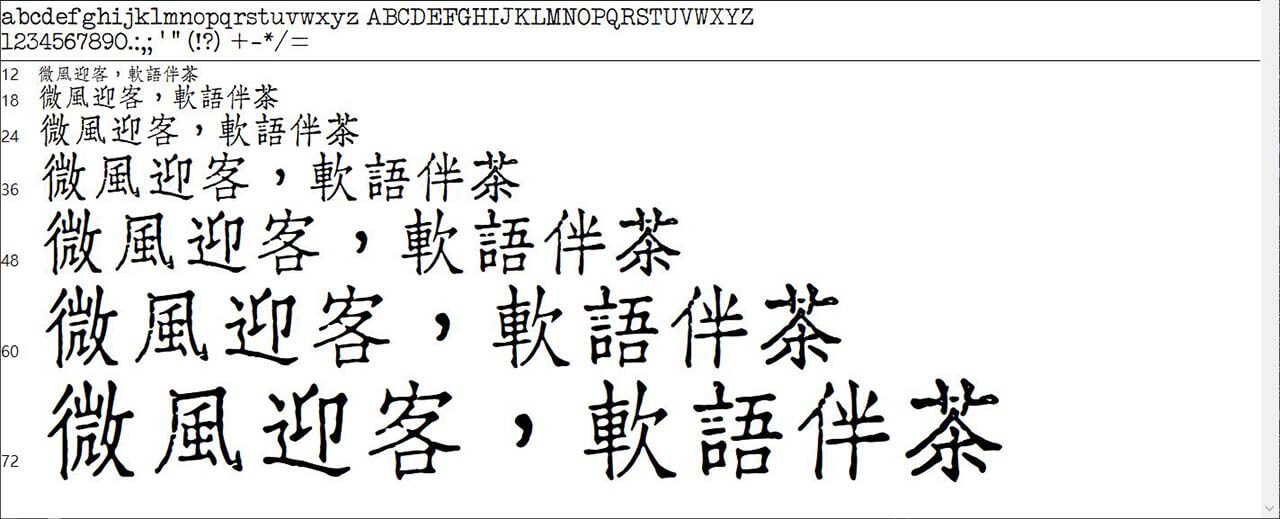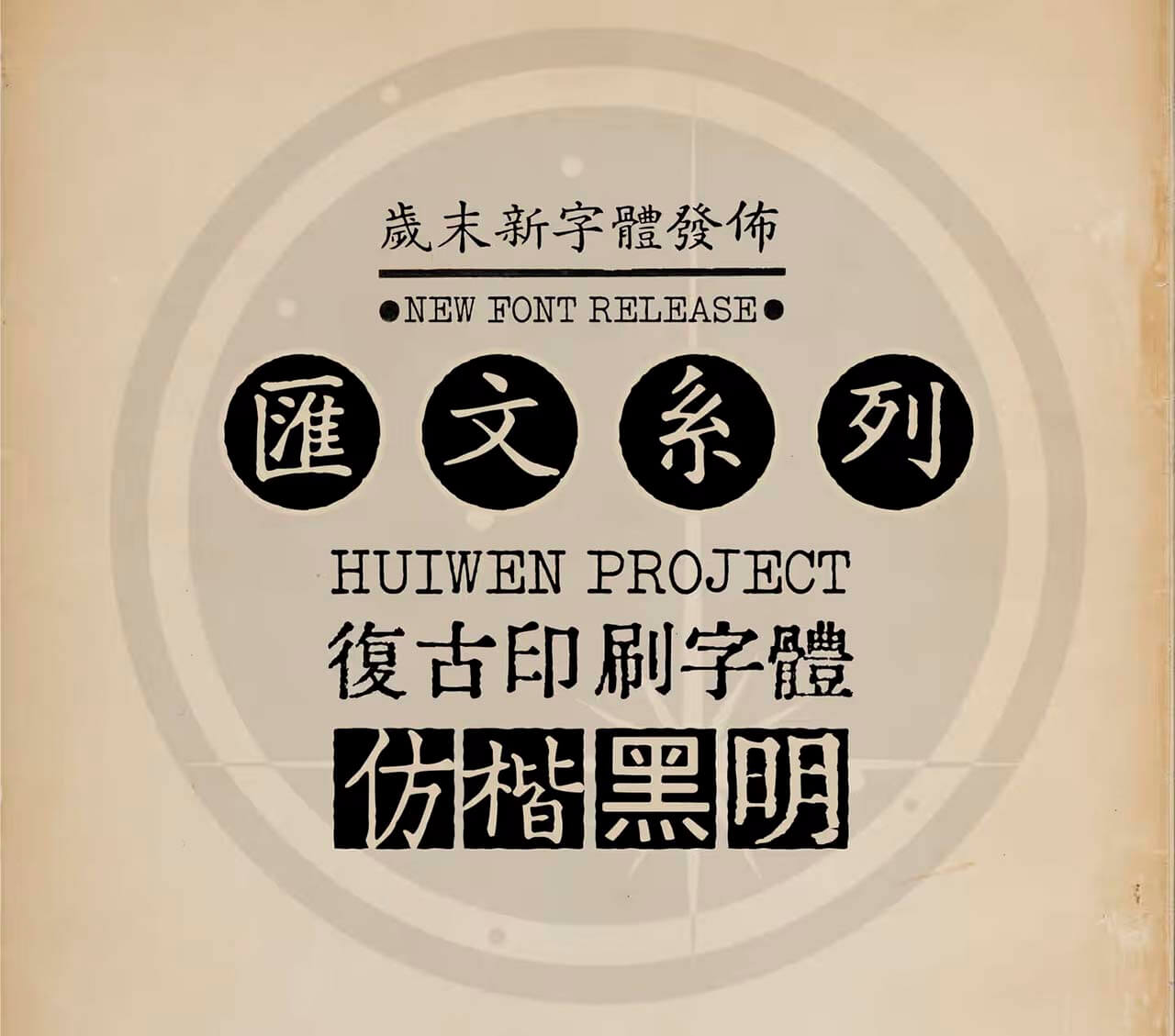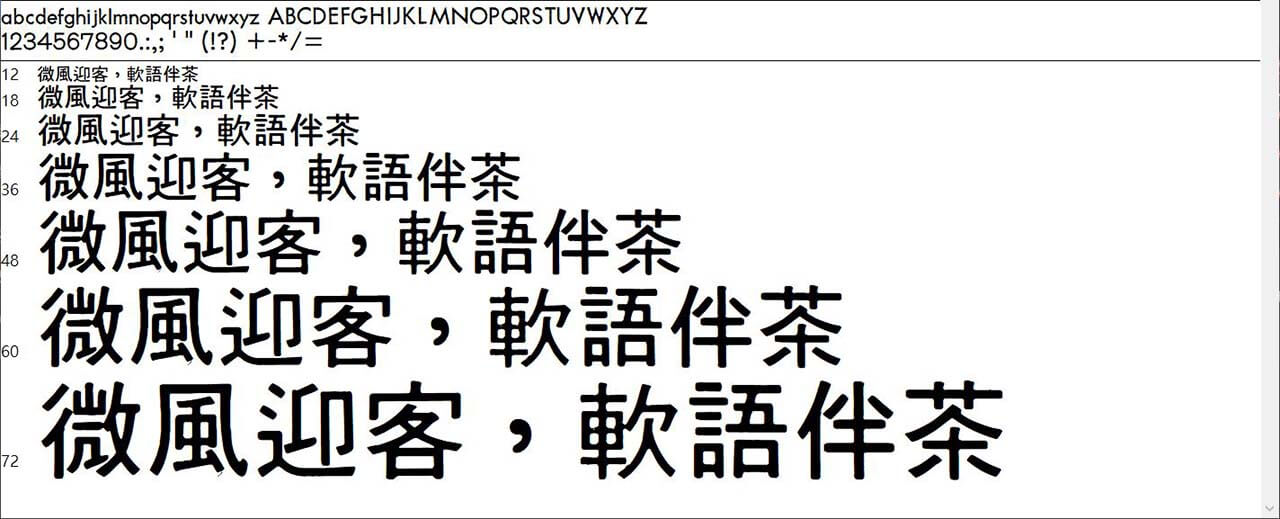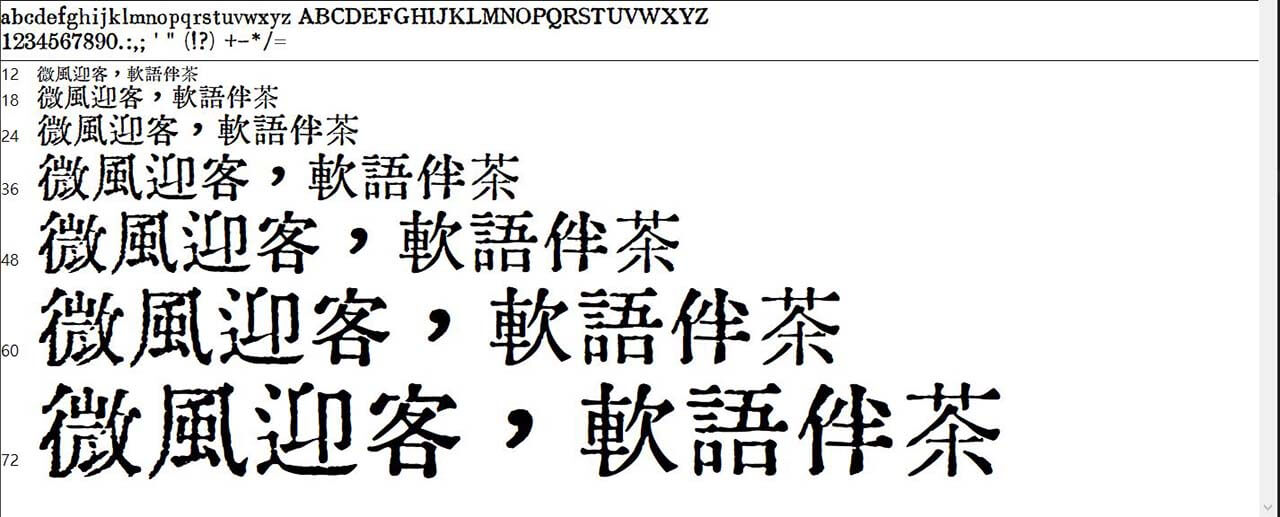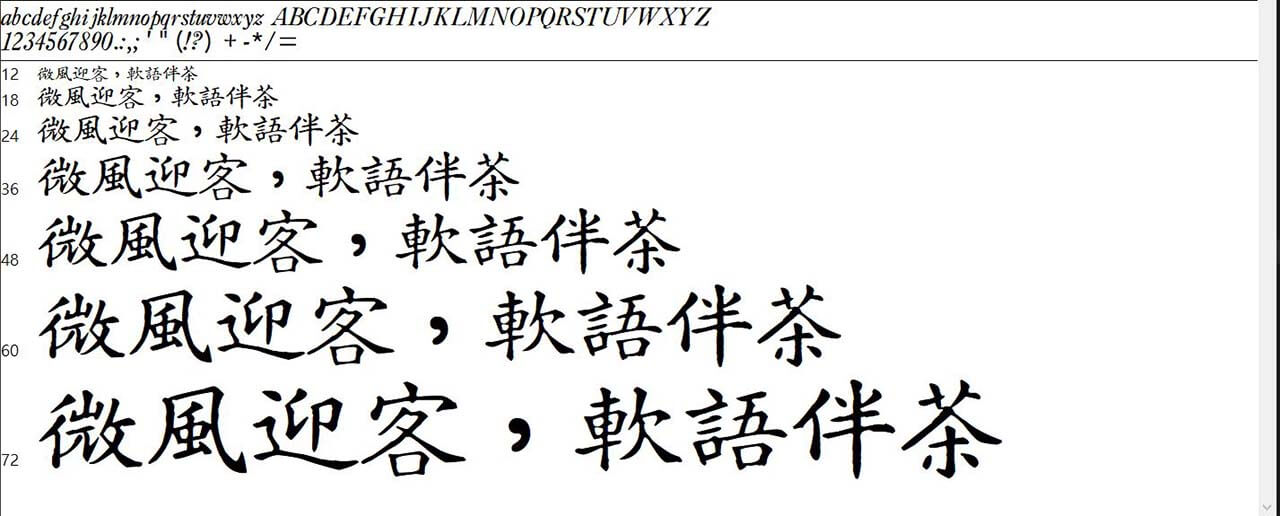
四款免費可商用「匯文字體」系列:明朝體、仿宋體、正楷體和港黑體
開發者特里王累積收集了各地鉛字,于 2021 年發布首款的「滙文明朝體」。接著再歷時兩年多,陸續又收集了正楷、仿宋的鉛字,以及香港照相排版的黑體字模板,再添加了這三款字型。終於在 2024 年底完成了「仿楷黑明」四款基礎字體,費時又費力,相當不容易的工作。這四款字體均具有印刷鉛字效果,並且採免費商用的字型授權方式。
四款匯文字體
• 匯文明朝體
匯文明朝體的字形主要來自于五、六十年代官方各種漢字改革文件。簡體字部分是復原五、六十年代書籍印刷樣貌。繁體字、傳承字部分則還原民國至共和國初期字形樣貌。這款字體是比較原汁原味的舊鉛字印刷風格。
匯文明朝體
• 匯文正楷體
匯文正楷體的來源是中國第一套完整的正楷活字「漢文正楷」,方正字庫也曾復刻過這套字,而特里王版本的不同之處,在於取較小的四號字來復刻,而不像其他復刻版是取自字稿或初號大字。
匯文正楷體
• 匯文仿宋體
匯文仿宋體的字形主要來自新華字模廠的老59-4仿宋體,而59-4仿宋則改刻自「華豐眞宋」。華豐真宋可說是中國各類仿宋體的祖先,大部分中國現在使用的仿宋體,都是基於華豐真宋修改而成。
匯文仿宋體
• 匯文港黑體
匯文港黑體主要參考自「照相排版」時期,香港廣泛使用的港版「岩田黑體」。此款黑體在香港的報紙雜誌、電影電視、平面招貼等各種地方都被廣泛使用。港版黑體跟日本原版(写研岩田ゴシック)或台灣版黑體相比起來,有很多的不同特點。照相排版讓人想起大學時代的系刊編輯日子。
匯文港黑體